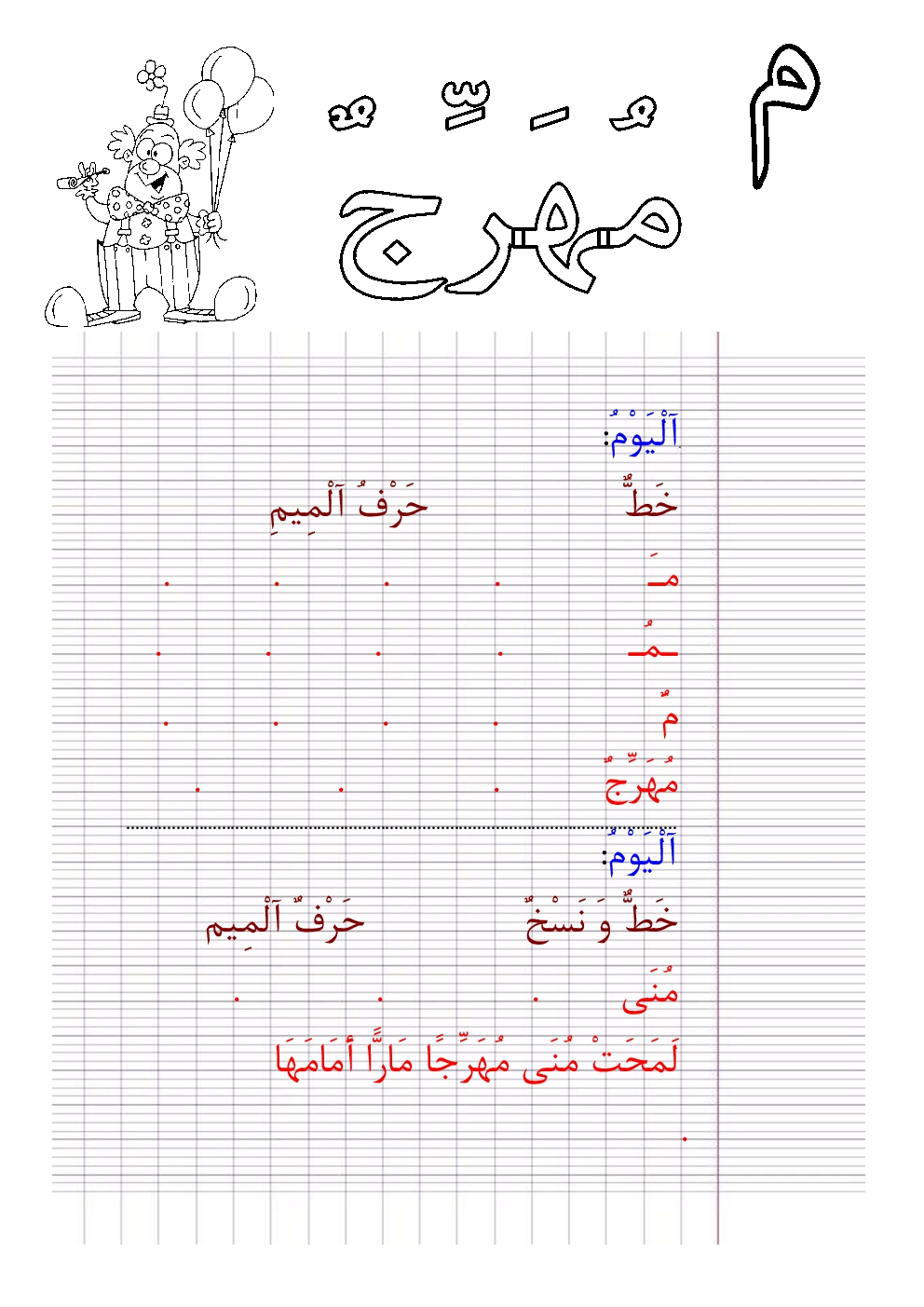
تحسين الخط للاطفال
تحسين الخط العربي هو مشكله تقابل الكثير منا الذي يعاني من سوء خط ابنه أو ابنته ومن منا يريد أن يجعل ابنه من اصحاب الخطوط الجميله وقال علي بن أبي طالب رضي الله عنه : ( عليكم بحسن الخط فإنه مفاتيح الرزق ) ولذلك نقدم لكم كتاب اليوم الذي يقوم بمحاولة تقويم الخط وجعله سلسا جميلا ويعتمد في ذلك علي استراتيجية جميله وسهله وهي التدريب علي شكل الحرف الصحيح والسليم وبعدها كتابة جمل وتكريرها علي الحرف تلك الجمل تحتوي علي شكل الحرف اول ووسط واخر الكلام . نترككم الان مع مواصفات الكراسة وتحميلها ..
محتويات كراس تحسين الخط للاطفال
- - تعليم الاطفال الكتابة بخط حسن
- - تقوية معجم الاطفال اللغوي من خلال الكلمات مع صور مرتبطة بها
- - التمييز بين الحرف اول ووسط واخر الكلام
- - كتابة جمل كاملة لمعرفة طريقة كتابة الحروف وسط الجمل بشكل جميل